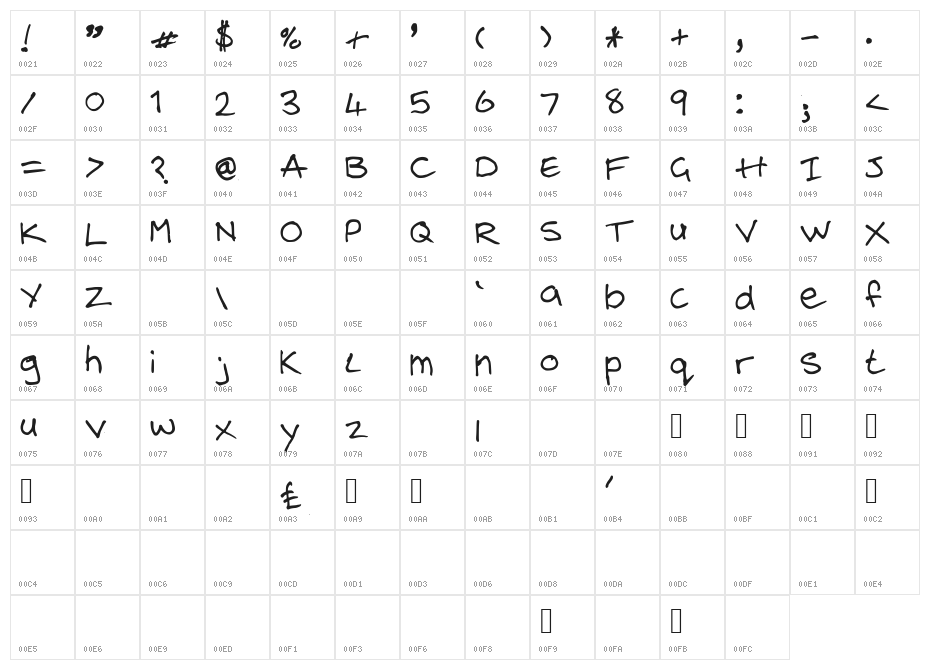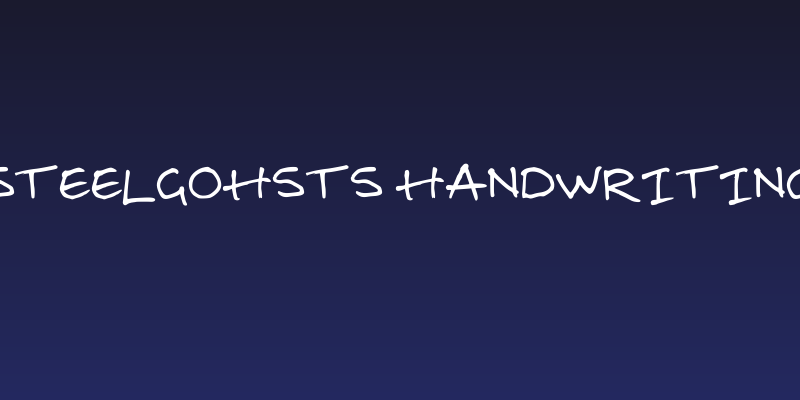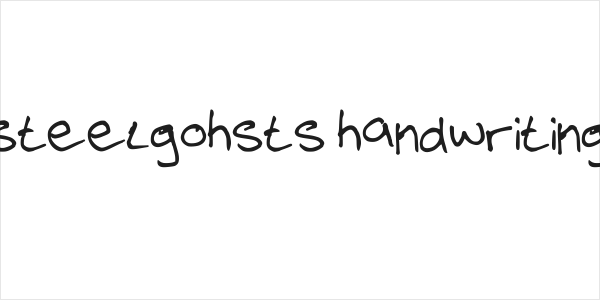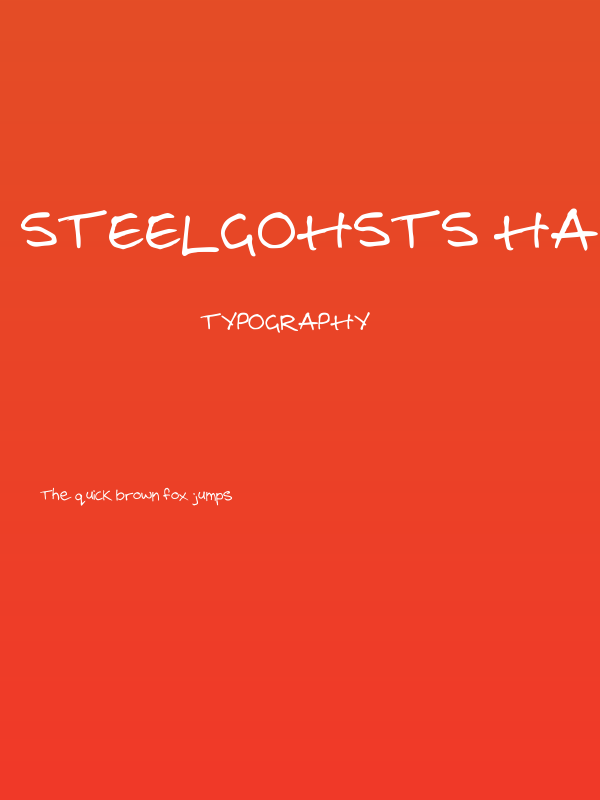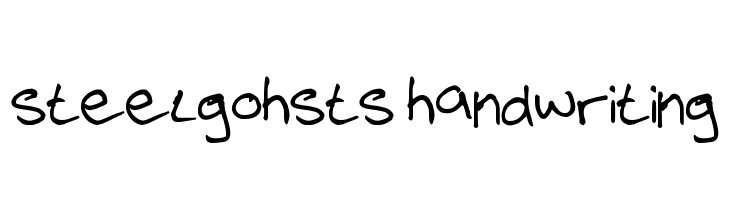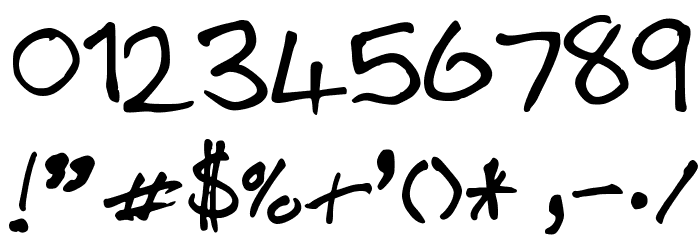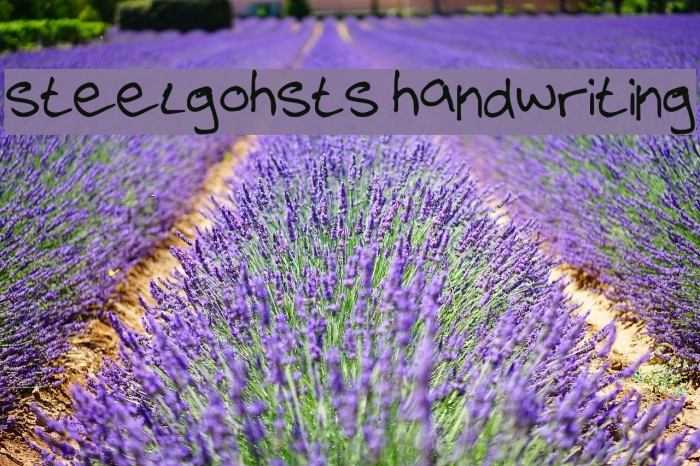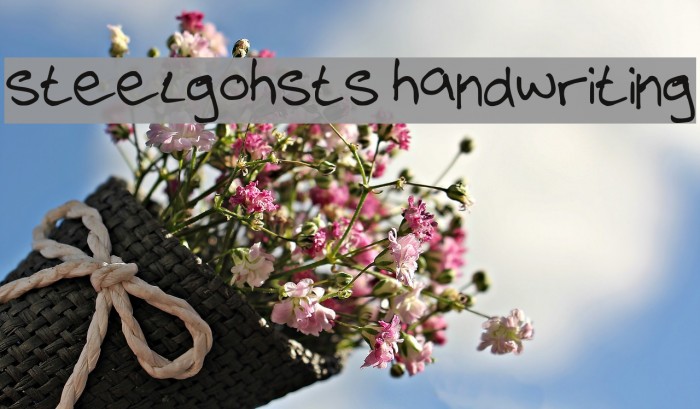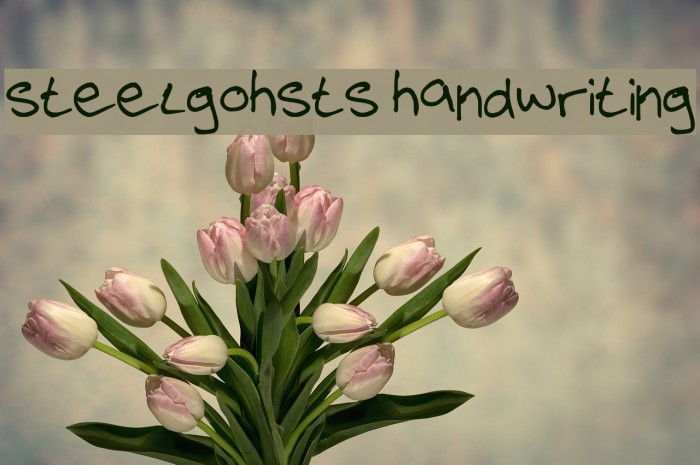
steelgohsts handwriting Font
| Style général | Casual |
| Cas d'utilisation | Invitations, Greeting cards, Personal notes |
| Projets proposés | Ideal for personal notes, invitations, greeting cards, and informal branding projects. |